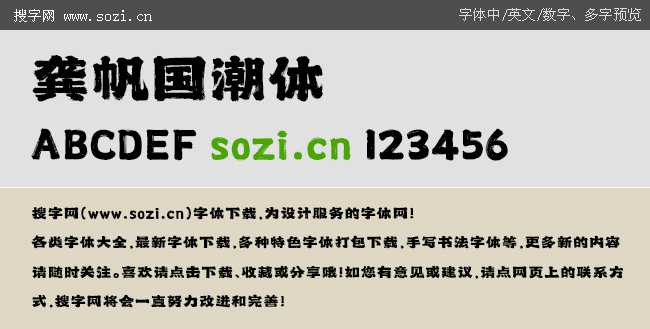
龔帆國潮體
搜字網(wǎng)給大家提供一款龔帆國潮體中文字體下載,該字體是一款非常個(gè)性的手寫書法字體,字體書寫時(shí)簡潔大方,流暢自然,給人一種豪放大氣的視覺感受,適用于平面宣傳設(shè)計(jì)、網(wǎng)頁設(shè)計(jì)、海報(bào)設(shè)計(jì)等應(yīng)用(淘寶搜龔帆字庫可買單字授權(quán))。